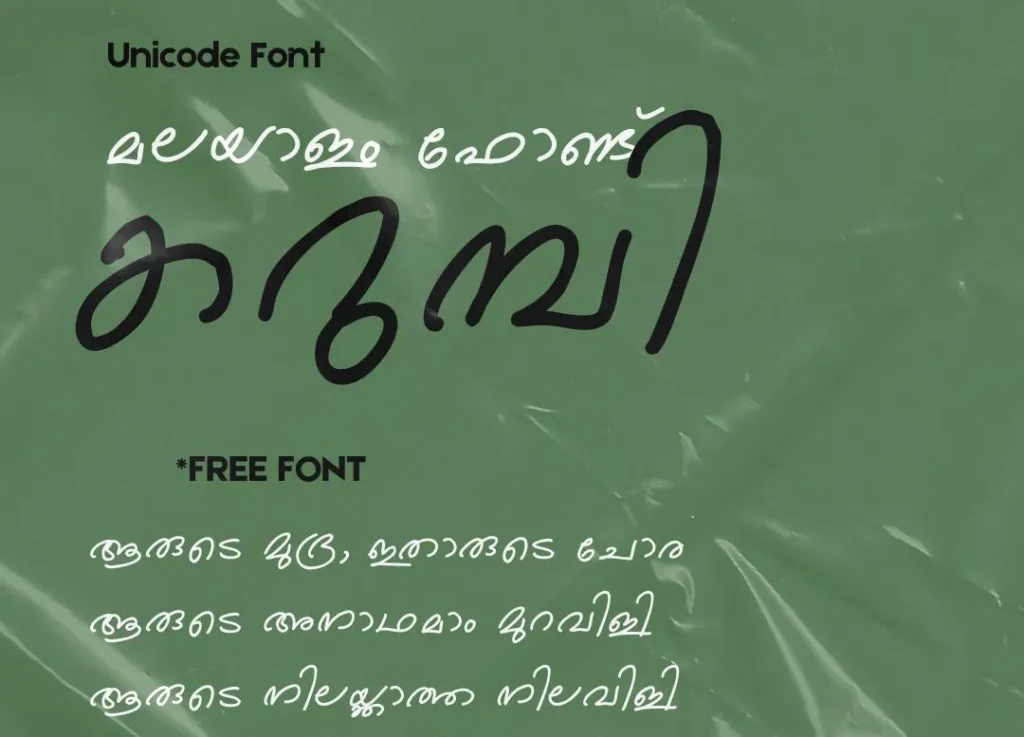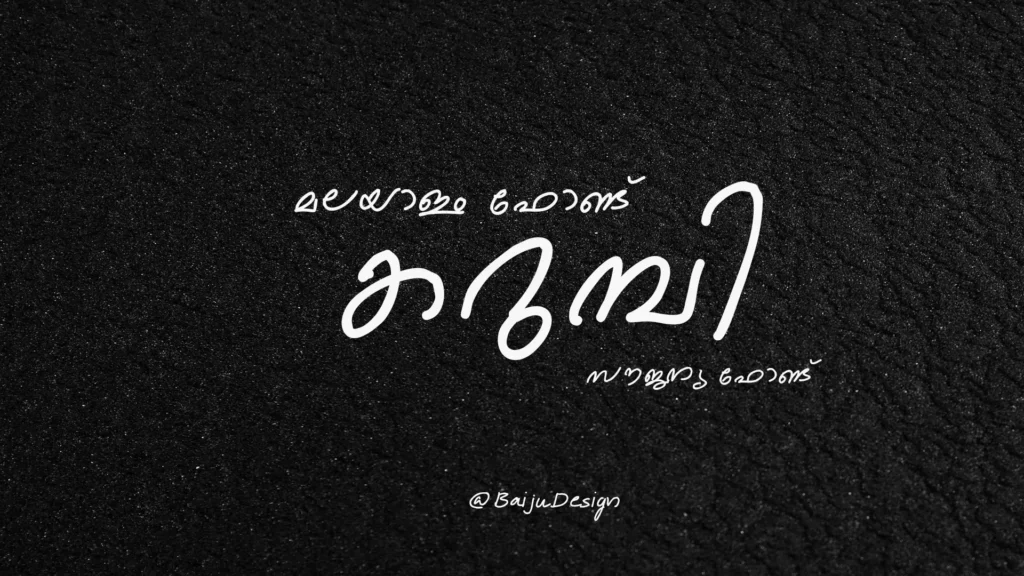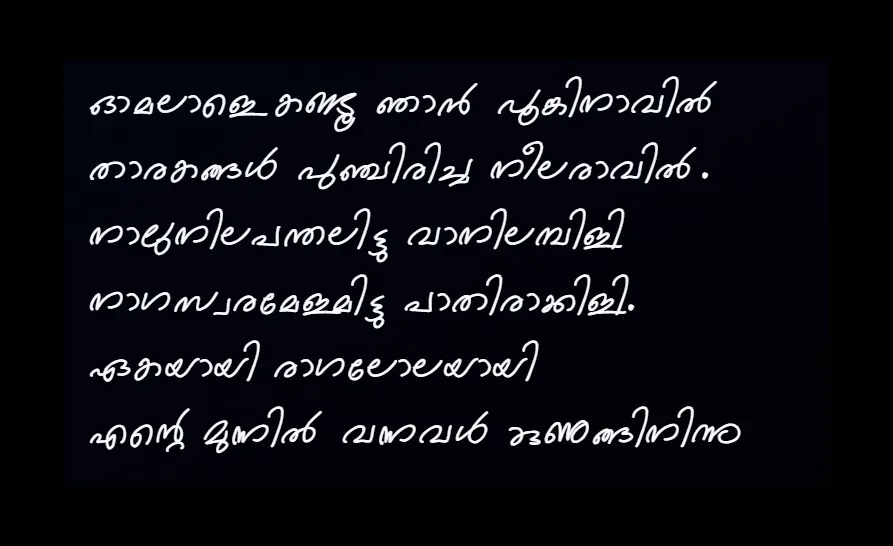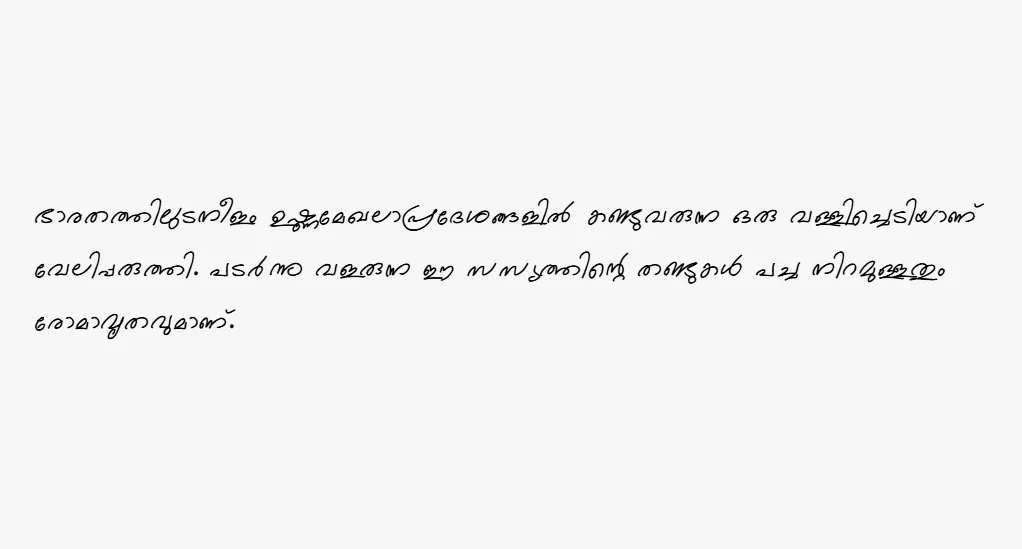
കറുമ്പി: ഒരു ഫ്രീ മലയാളം ഫോണ്ട് | Karumbi Malayalam Font
മലയാളം ഡിസൈൻ രംഗത്ത് ഒരു പുതിയ സംഭാവനയായി കറുമ്പി ഫോണ്ട് പിറവിയെടുത്തിരിക്കുന്നു. SMC (Swathanthra Malayalam Computing) ഒരുക്കിയിരിക്കുന്ന ഈ ഫ്രീ ഫോണ്ട്, മലയാളം ഭാഷാ പ്രേമികളുടെയും ഡിസൈനർമാരുടെയും ശ്രദ്ധ ആകർഷിക്കുന്ന ഒന്നായി മാറിയിരിക്കുന്നു.
ഫോണ്ടിന്റെ പ്രത്യേകതകൾ:
• പേരിൽ തന്നെ സവിശേഷത: കറുമ്പി എന്ന പേരിൽ തന്നെ ഒരു മലയാളത്തിന്റെ നാടൻ മനം മറഞ്ഞു നിൽക്കുന്നു. ഫോണ്ടിന്റെ രൂപകൽപ്പന തികച്ചും സുന്ദരവും, പാഠ്യശൈലിയ്ക്ക് അനുയോജ്യവുമാണ്.
ഇത് എങ്ങനെ ഉപകരിക്കും?
മലയാളം ലേഖനങ്ങൾ, പോസ്റ്റർ ഡിസൈനുകൾ, ബാനറുകൾ, പാഠപുസ്തകങ്ങൾ എന്നിവയിൽ കറുമ്പി ഉപയോഗിക്കുന്നത്, ഒരു പൂർണ്ണമായ ഭാഷാ അനുഭവം നൽകുന്നു.
Karumbi is a Malayalam font crafted specifically for impactful titles. This elegant typeface brings a touch of sophistication to your designs, making headlines truly stand out.